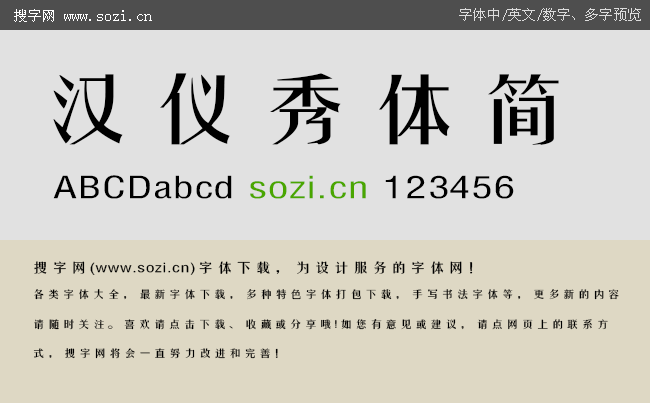
漢儀秀體簡(jiǎn)
搜字網(wǎng)給大家提供一款漢儀秀體簡(jiǎn)體中文字體下載。漢儀秀體字形結(jié)構(gòu)穩(wěn)定,配合設(shè)計(jì)簡(jiǎn)潔的筆畫(huà),排版時(shí)整體線性效果更加突出,使閱讀更加流暢。 筆畫(huà)風(fēng)格上融合了黑體與宋體的特征,線條簡(jiǎn)潔,氣質(zhì)圓柔、秀美,風(fēng)格靈動(dòng)、時(shí)尚。筆畫(huà)間的相互呼應(yīng)更使得字體整體結(jié)構(gòu)統(tǒng)一完整、避免了結(jié)構(gòu)的呆板、生硬?蓱(yīng)用于平面設(shè)計(jì)、出版印刷、廣告設(shè)計(jì)、包裝設(shè)計(jì)等領(lǐng)域。